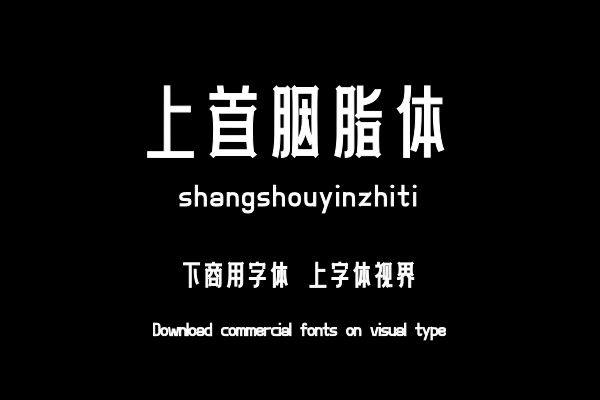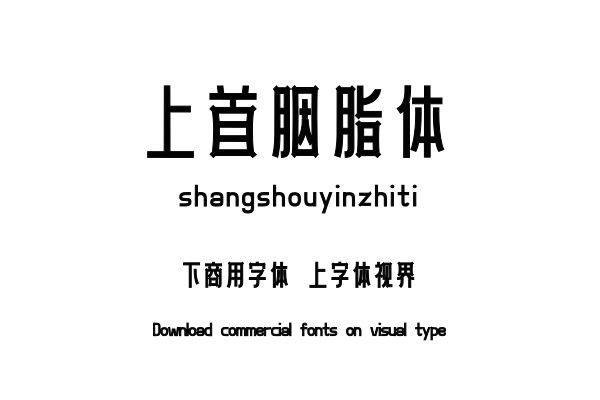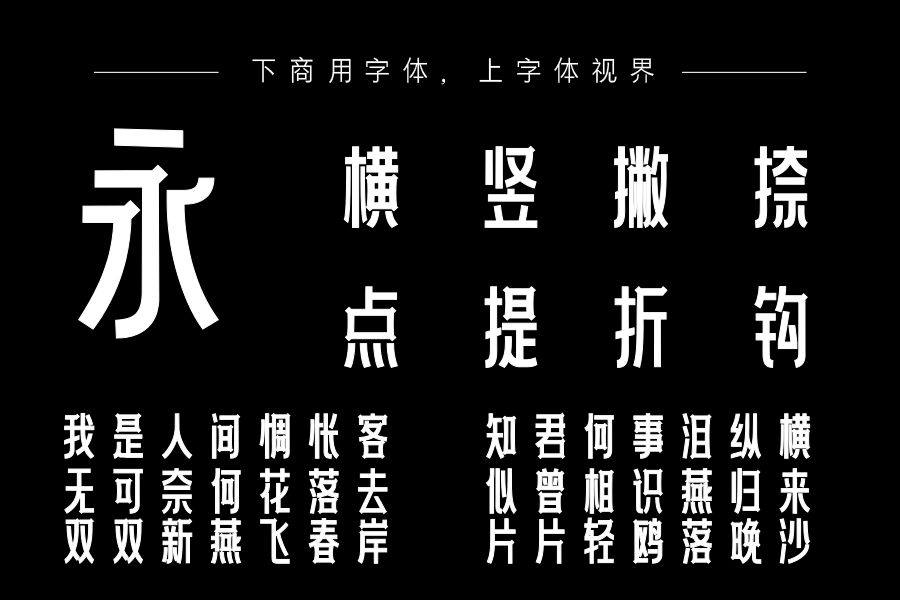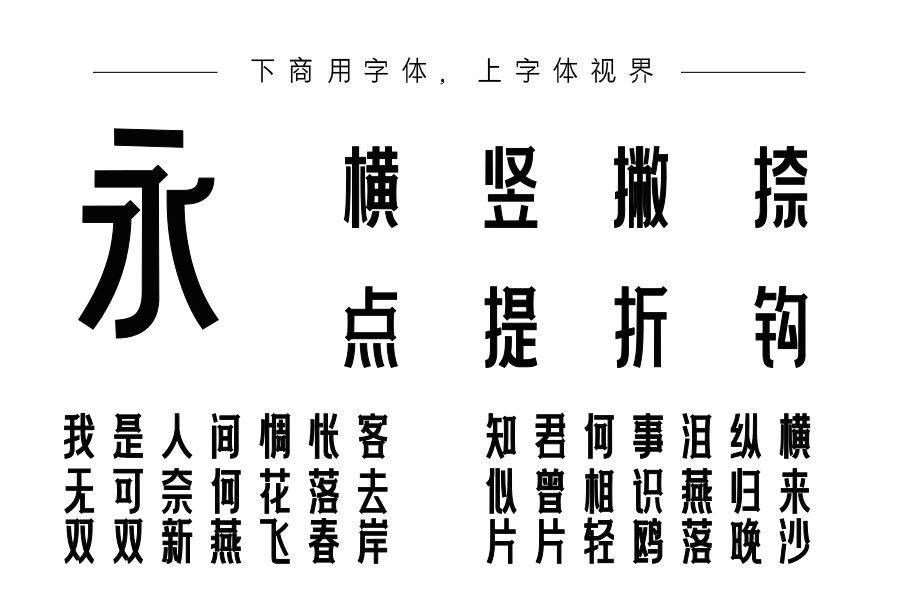
上首胭脂体,字体外形偏向方正规整,字形细长秀气。笔画粗细一致,字体外形整体更加统一。形态上富有创意,在字体笔画交接处设计了特点,这让字体更加具有辨识度和艺术特色......购买须知:“下载服务费”与“字体VIP”所获得字体 仅用于个人非商用, 商用请联系付费授权。本字体为电脑用字,手机没有root权限不支持直接手机换字(手机如何root,请自行百度搜索教程)。购买前请先 了解清楚后再付款 ,字体为虚拟产品无法回收 一旦购买不支持退款。